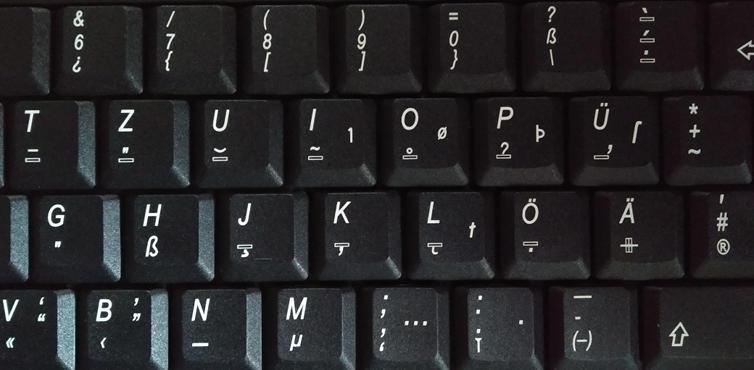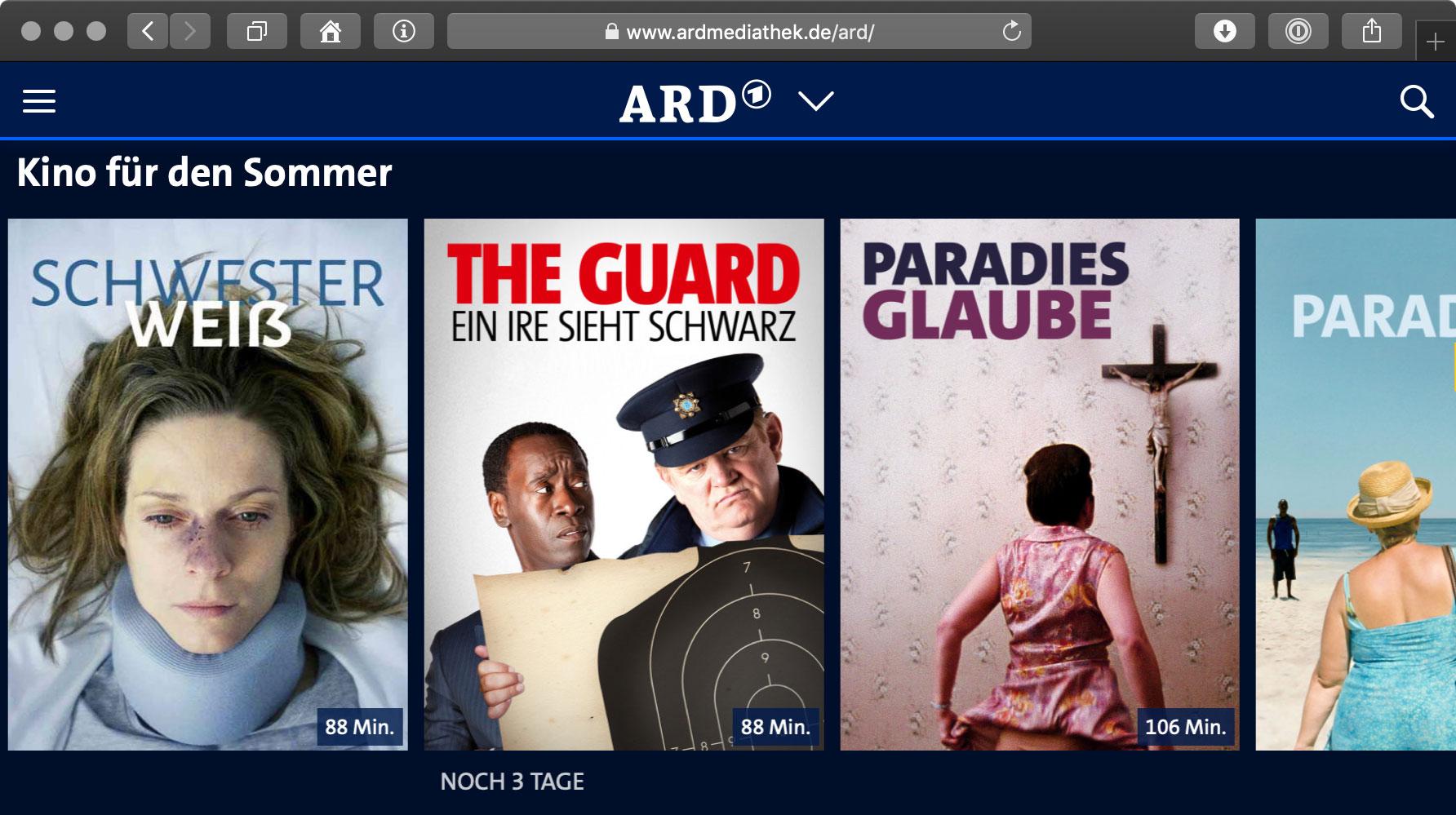
Meine Gedanken waren da eher bei Schrift als bei Verkehr. Und daß wir uns der Kurrent per Verordnung
des PG   Bormann    entwöhnt haben, muß ja nicht unbedingt so bleiben.  Die Erkenntnis, daß nichts Bestand hat,
außer dem Wandel, ist mir auch bekannt. Insofern ist Veränderung und ständige Anpassung nur normal. Auch bei Schrift
und Sprache. Dessen ungeachtet halte ich die Kurrent in der um 1900 gebräuchlichen Form für eine tolle Schrift,
die, gekonnt ausgeführt ein bestechendes  Bild ergibt. Und dank Bismarck etwas charakteristisch Deutsches  geworden ist.
Der hielt übrigens andere  Schriften für " Kringelei". So weit gehe ich nun nicht. Wie auch "andere Mütter schöne Töchter"
haben, haben auch andere Kulturen tolle Schriften entwickelt. Aber deshalb muß ich mir die doch nicht  unbe-
dingt zu Eigen machen, wenngleich ich sie als Kulturgut respektiere. La.
muß ja nicht unbedingt so bleiben
Wird es aber: Globalisierung und Digitalisierung sind zwei Faktoren, die die Kurrent sowieso getötet hätten.
haben auch andere Kulturen tolle Schriften entwickelt
Und dennoch bedienen sich alle des (mehr oder weniger) lateinischen Alphabets, wenn es um interkulturelle Kommunikation geht.
Deshalb sehe ich da eigentlich auch keine Notwendigkeit für ein neues  Zeichen.
Keine Notwendigkeit für ein Versal-Eszett? Wie oft wurde eigentlich schon darauf hingewiesen, dass mit diesem Zeichen endlich die richtige Schreibung von bestimmten Eigennamen möglich ist, zum Beispiel bei der Verwendung von Versalien im Personalausweis oder bei Kapitälchen in Literaturverzeichnissen? Und natürlich ist nur mit dem Versal-Eszett eine eindeutige Rückauflösung von »SS« zu »ß« bzw. »ss« möglich.
Nachdem Du schon Bormann in den Verlauf gebracht hast, kann ich ja entsprechend Godwin das "geliebte Führerlein" auch noch bringen:
Aus einem Schreiben des Reichsministers der Reichskanzlei: „Der Führer hat sich für eine Beibehaltung des „ß“ in der Normalschrift entschieden. Er hat sich aber gegen die Schaffung eines großen „ß“ ausgesprochen. Bei der Verwendung großer Buchstaben soll das „ß“ vielmehr als „SS“ geschrieben werden.“
Danke für den Hinweis. War mir so nicht bekannt, erklärt aber so Einiges!  Ich hatte da
meinen Lehrer aus Hermannsburg  im  Hinterkopf. Und der hatte für  "diese Sippschaft"
rein gar nichts über. Weshalb er auch gerne die Kurrent als "Umgangsschrift" gesehen
hätte. Er schrieb sie , obwohl der "Latein" kundig, aus "Überzeugung und Prinzip"
munter weiter." Die" hatten "anderweitig schon genug Unheil angerichtet", da wollte
er, so gut er konnte "dagegenhalten".
Hannah Häußer und Maximillian Borchert haben alle Google-Fonts (zum Stand August 2017) nach ihrem Eszett abgeklopft, sortiert, verknüpft und möglichst vergleichbar aufgearbeitet. Alle Schriften sind mit ihrem Regularschnitt in 10 pt Schriftgröße und mit 13 pt Zeilenabstand dargestellt. Ergänzend dazu gibt es beschreibende Infos zum Font, Querverweise zu Schriftfamilien-Mitgliedern sowie einige Vorschläge zur neuen Glyphe.
Auf den rechten Seiten findet man die »Stars« des Buches in großer Darstellung präsentiert: Eszett-Zeichen, Seiten für Seite, in ca. 400 pt Schriftgröße. Von den 400 Schriften sind 86 bereits mit ihrer großen Eszett-Glyphe vertreten.
niße
Ah, ok, ja – das könnte sein! Ich habe es automatisch „niiiiieeeße“ gelesen und das Wortspiel (wenn’s denn eins war) nicht verstanden. :oops:
Ich hab auch "nisse" gelesen, zumal der Rest des Titels auf Deutsch ist …
Tja, das ging in die Hose. Vielleicht wäre »wärri neiß« verständlicher  gewesen?
Es erstaunt mich einigermaßen, wie lange sich dieses Thema nun schon "hält".   Die Firma ßeitenbacher  ist wohl noch nicht lange           genug  " in Aller Munde"  .   Sonst hätte man doch längst der Notwendigkeit entsprochen, und einen Großbuchstaben  kreiert.
Sonst hätte man doch längst der Notwendigkeit entsprochen, und einen Großbuchstaben  kreiert.
Warum der Konjunktiv? Man hat der Notwendigkeit ja mittlerweile entsprochen.
Und Diskussionen um Probleme halten sich eben so lange, bis letztere gelöst sind.
Ja, erinnere mich, daß es immer hieß," gut Ding will Weile haben".  Manches braucht dann
wohl etwas  mehr Weile.  Oder liegt's    an der Vielzahl der  " Köche"?
Die Regel bezog sich auf das  SYRIA-Markt- Plakat mit der missratenen  Königsstraße.
Nämlich die, daß Deutsch so geschrieben wird, wie's gesprochen wird. Wenn  man
dann der Sprache nicht so richtig mächtig ist, weil man  als Vorbilder in der
Mehrzahl Leute hat, deren Gebrauch der Sprache  mit oberflächlich noch
zurückhaltend  bezeichnet ist. darf wohl kein anderes  Ergebnis erwartet werden.
Nur einen kleinen, optischen Wermutstropfen hat dieses Modell (Triggerwarnung!):
Wer’s nicht gleich erkennt, möge unten klicken, aber nur bei sehr starken Nerven: